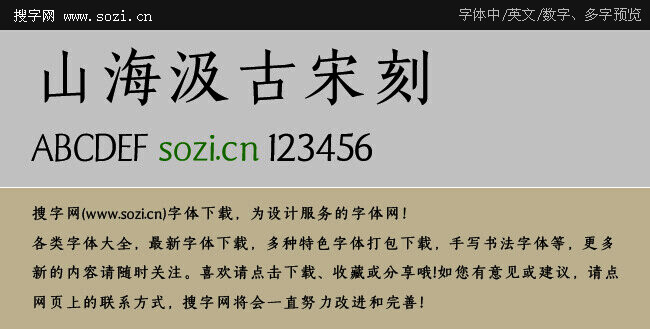
山海汲古宋刻
搜字網(wǎng)提供一款山海汲古宋刻中文藝術字體下載,山海汲古宋刻是一款國風復古刻本字體,包含簡體漢字6763個,字形秉承中國宋代古籍善本之字形特性,版刻刀法剔透,字形方正,起落頓筆有棱角。筆刀結合剛柔并濟。在秉承筆形間創(chuàng)新,結合當代設計視覺環(huán)境,融入現(xiàn)代審美,適用場景更多元,筆畫造型清晰銳利,刪繁取簡,筆鋒凌厲,速度感強,粗細對比強烈,重現(xiàn)刀刻古韻之美。適合包裝設計、海報設計、廣告設計等應用。